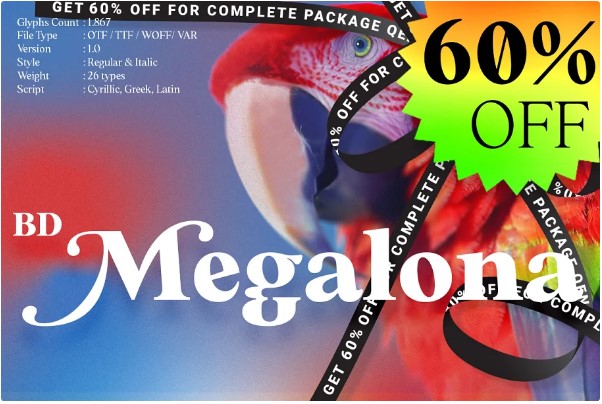
Основополагающим в создании этого шрифта является реализация нашего интереса к типографике за последний год. Вдохновившись элегантностью, последовательностью и трудолюбием Times New Roman, мы вышли на пугающий чистый холст и начали думать о том, что нужно сделать, чтобы продвинуть эту идею еще дальше. Что бы ни пришло нам в голову и когда оно выльется наружу, оно обязательно останется в рамках правил начертания букв.
Этот шрифт создан благодаря тщательному подходу, настойчивости и полной завершенности. Вкус, корректировка форм и эксперимент - вот три слова для этого шрифта. Она родилась большой и очаровательной, имеет расширенный набор из более чем 1800 глифов, охватывающий 219 языков с использованием латинского, кириллического (от базового до расширенного) и греческого алфавитов. Включены расширенные возможности открытого шрифта, такие как стилистические альтернативы, терминальная форма, сваш, произвольные лигатуры, ординаты, маленькие прописные буквы, позиционные числа, дроби и формы с учетом регистра.
BD Megalona предоставляет широкий выбор вариантов, которые придадут роскошные вибрации в симметричных макетах с выборочными отклонениями, и хорошо подойдут для стильного вида вашего типографского проекта. Это полный пакет решений проблем, идеально подходящий для основного текста и высокоэффективных заголовков. Передовые возможности открытого шрифта определенно потрясают на логотипах, брендинге, журналах, веб-сайте и т.д.
BD Megalona - это наше эго в выражении, которое стремится обеспечить необходимость дизайна в наши дни, оставаясь при этом в коридорах славы прошлых традиций как источника нашего вдохновения.